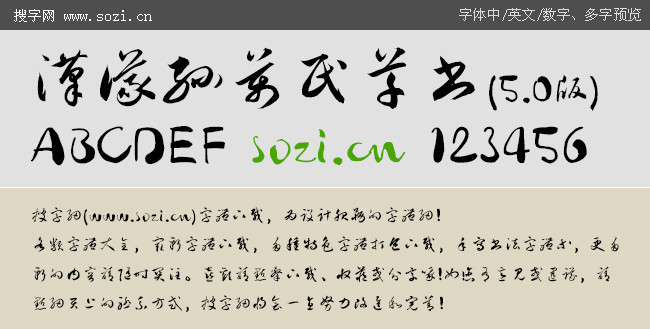
漢儀孫萬民草書5.0
搜字網(wǎng)提供一款漢儀孫萬民草書5.0中文字體下載,漢儀孫萬民草書字體是一款應(yīng)用于藝術(shù)設(shè)計(jì)方面的簡體中文字體,該字體筆畫粗壯,尾部的甩尾有力且有豐富的筆觸細(xì)節(jié),大字效果突出且引人注目;并且最大程度還原作者書寫字形,細(xì)節(jié)表現(xiàn)完整,且字庫完整,可以廣泛應(yīng)用于名片設(shè)計(jì)、新聞媒體、宣傳海報(bào)、ppt、影視制作以及內(nèi)容用字等領(lǐng)域。(本字體為個(gè)人非商用版,如需要商用請聯(lián)系漢儀公司購買版權(quán))